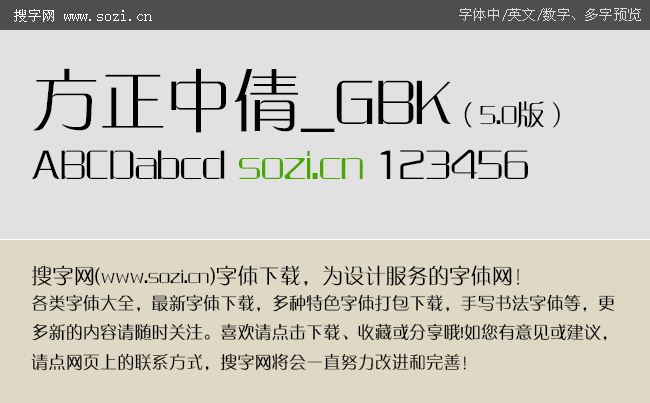
方正中倩-GBK
搜字網(wǎng)給大家提供一款方正中倩簡體下載。GBK標(biāo)準(zhǔn)收錄字體更全,中倩體親切、幽雅、柔美和華麗,筆劃粗細(xì)對比適中,婉轉(zhuǎn)嫵媚,溫順乖巧,看似平淡無奇,卻能給人以美的感受。適用于個(gè)人用品、化裝品、食品、家居廣告宣傳使用環(huán)境。